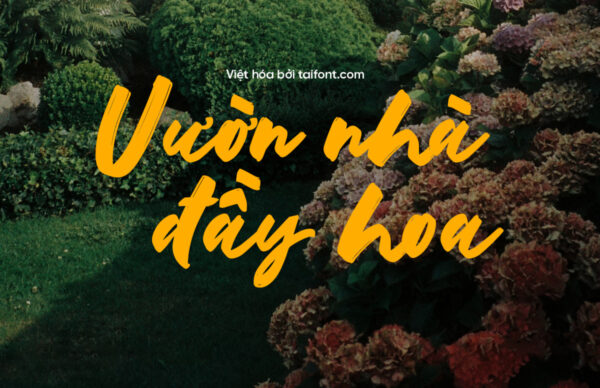
Giới thiệu về Font TF Amorfati Việt hóa
TF Amorfati Việt hóa là một font chữ Brush độc đáo, nổi bật với thiết kế to, đậm và đầy ngẫu hứng. Font này mang đến vẻ ngoài phóng khoáng, tự do và rất riêng, gợi cảm giác về những nét cọ được phẩy một cách tự do, đầy năng lượng. Đây là lựa chọn lý tưởng để tạo điểm nhấn thị giác mạnh mẽ và gây chú ý ngay lập tức, đặc biệt trong các thiết kế liên quan đến mỹ phẩm, thời trang và yoga.
Với đặc điểm là nét brush to đậm, dứt khoát và tính thẩm mỹ cao, Amorfati là lựa chọn hoàn hảo cho các thiết kế muốn truyền tải sự mạnh mẽ, hoài niệm và sự độc đáo, đặc biệt là trong các lĩnh vực:
- Thiết kế mỹ phẩm: Hoàn hảo cho bao bì, nhãn mác, hoặc các ấn phẩm quảng cáo của các sản phẩm làm đẹp, mỹ phẩm. Font này giúp truyền tải vẻ đẹp tinh tế, sang trọng và độc quyền của sản phẩm, nâng tầm giá trị thương hiệu.
- Thiết kế thời trang: Lý tưởng cho thương hiệu thời trang, phụ kiện, từ logo, nhãn mác sản phẩm, đến các lookbook và chiến dịch quảng bá bộ sưu tập. Nét chữ độc đáo của font giúp tạo dấu ấn cá nhân, sự phá cách và độc đáo cho thương hiệu.
- Thiết kế yoga: Phù hợp để sử dụng trên poster, banner, áp phích quảng cáo các lớp học yoga, hoặc các sản phẩm liên quan đến thiền, lối sống lành mạnh. Font này giúp truyền tải vẻ đẹp ngẫu hứng, tự do và đầy năng lượng của bộ môn yoga.
- Thiết kế poster và banner: Tuyệt vời để tạo các tiêu đề chính (headline), slogan, hoặc thông điệp quảng cáo trên poster, banner, hoặc bất kỳ ấn phẩm nào cần sự chú ý tối đa. Nét chữ tự nhiên của font giúp thông điệp của bạn nổi bật, dễ đọc và truyền tải một cách hiệu quả.
Với TF Amorfati Việt hóa, bạn có thể dễ dàng thổi hồn mạnh mẽ, sự độc đáo và cá tính vào các thiết kế, tạo ra những sản phẩm không chỉ đẹp mắt mà còn cực kỳ ấn tượng và có khả năng thu hút sự chú ý tối đa.
Font Việt hóa TF Amorfati